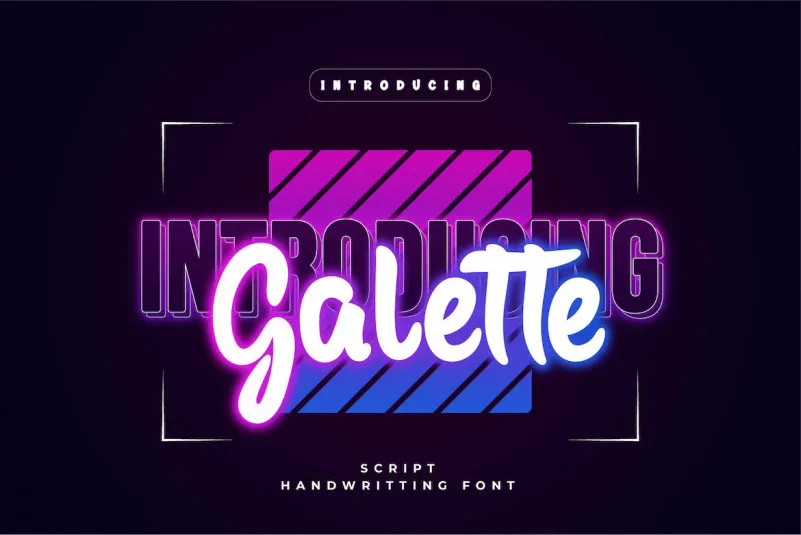
Galette Font – Download Grátis
A fonte Galette é uma criação cuidadosamente projetada para capturar a essência das letras escritas com delicadeza por mãos habilidosas e elegantes, inspirando texturas suaves e sutis que se destacam especialmente nas partes mais significativas de um projeto gráfico. Suave ao ponto de proporcionar o toque personalizado de uma mão humana sobre a sua produção de design especial, essa fonte é perfeita para adicionar um toque único em suas letras do texto ou cabeçalhos. Productype, o designer responsável pela Galette Font, tem como objetivo criar fontes únicas e inspiradoras que tornem cada projeto gráfico uma verdadeira obra de arte. Experimente a Galette Font para dar vida aos seus designs com essa mão humana, delicada e elegante.
Designer: productype